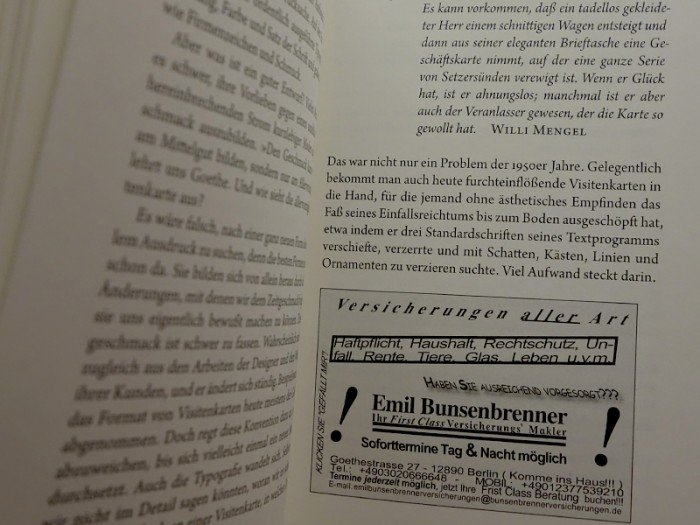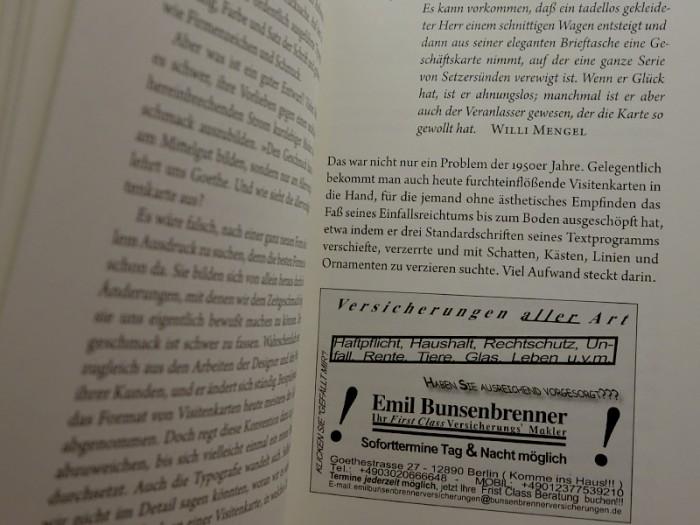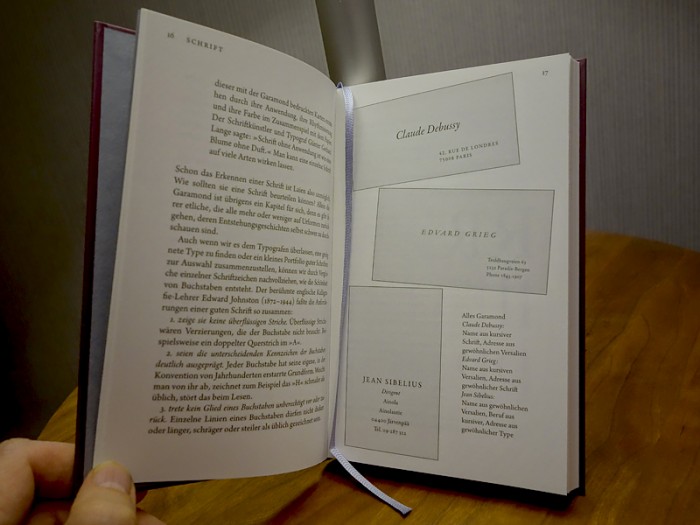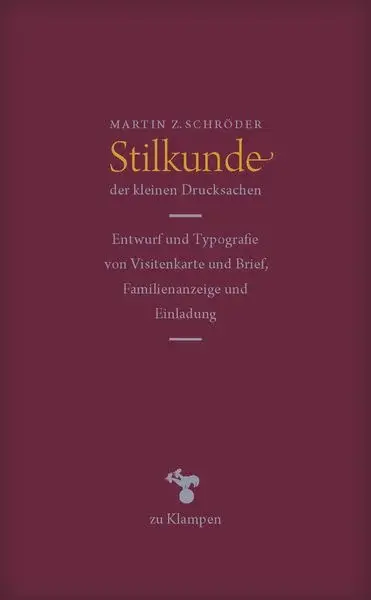
Klappentext: Kleine Drucksachen gehören zu den Accessoires des gesellschaftlichen Lebens. Sie verleihen bedeutenden Ereignissen Glanz. Wie man Schriften beurteilt und auswählt, passende Farben und das richtige Papier findet, wird in diesem Buch anschaulich beschrieben. Es enthält Entwürfe und Formulierungen für Geburts- und Todesanzeigen sowie Hochzeitseinladungen und plädiert ernsthaft wie unterhaltsam für konventionelle Handwerklichkeit.
Verlag: »You never get a second chance to make a first impression.« – Das gilt nicht nur für Äußerlichkeiten wie das Auftreten, die Kleidung oder Frisur. Auch Visitenkarten und Familiendrucksachen sind Äußerlichkeiten, doch sie verleihen unserer Persönlichkeit sichtbar Ausdruck.
Wurden solcherlei »Akzidenzen« einst bei einem erfahrenen Drucker in Auftrag gegeben, bedient man sich heute meist achtlos im Internet. Wer etwas auf sich hält, der scheut den geistigen und materiellen Aufwand für gelungene Drucksachen jedoch auch in unserer Zeit nicht, ahnt er doch, dass dieser sich lohnt.
Martin Z. Schröder erklärt in seiner »Stilkunde« anschaulich und unterhaltsam, was eine gut gestaltete Drucksache ausmacht, welche Schrift, welche Farbe, welches Papier zu welchem Anlass passen, wie Kleindrucksachen »diplomatische Dienste« leisten und Aufschluss über ihren Überbringer geben.
Autor: In diesem Buch fasse ich meine Erfahrungen aus über dreißig Jahren als auf Akzidenzen (Gelegenheits- oder Kleindrucksachen) spezialisierter Schriftsetzer, über 20 Jahren in einer eigenen Werkstatt, zusammen. Ich erzähle davon und zeige an Beispielen, wie Typografen Schriften anschauen, beurteilen, auswählen und auf Drucksachen anordnen. Ich stelle die Wirkung von Druckfarben dar und gebe Auskunft zu Klang, Griff, Farbe, Gewicht und Volumen von Papier. Einzelne Kapitel behandeln Visitenkarten, Briefpapier, Hochzeitsdrucksachen, Geburts- und Todesanzeigen und zeigen Entwürfe. Es finden sich Ausführungen zur Auswahl von und zum Umgang mit Handwerkern und Designern und es wird erklärt, wie Preise für deren Dienstleistungen gebildet werden. Am Ende des Buches finden sich Informationen zu Druckverfahren und eine Erläuterung von Fachbegriffen, die dem Laien das Verständnis typografischer Arbeit erleichtern.
Untertitel: Entwurf und Typografie von Visitenkarte und Brief, Familienanzeige und Einladung
Autor(en): Martin Z. Schröder